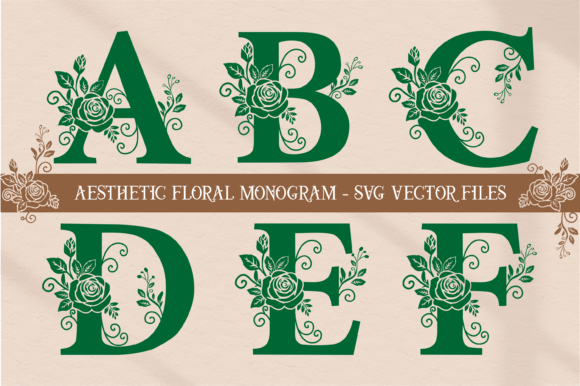
Elegant Floral Monogram SVG Alphabet
Jika anda sedang mencari aset berkualiti tinggi seperti Elegant Floral Monogram SVG Alphabet, pakej premium ini merupakan pilihan yang hebat untuk projek kreatif anda.
Sama ada anda mencipta produk POD (Print on Demand), jemputan perkahwinan atau grafik media sosial, Elegant Floral Monogram SVG Alphabet amat bersesuaian.